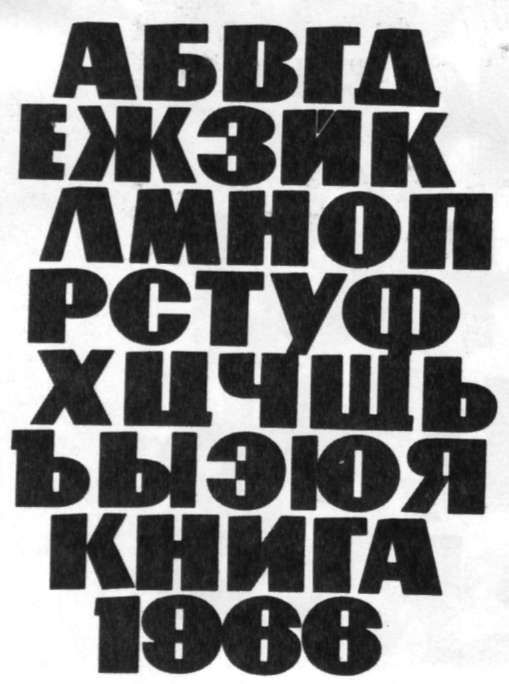
Доброго дня всем. Сегодня мы поговорим о шрифтах. И поговорим исключительно с практической точки зрения без внедрения в историю, без научных терминов и рассмотрения различных научных точек зрения на виды и подвиды шрифтов. Классификация шрифтов будет сугубо личной и субъективной, основаной только на собственном многолетнем практическом опыте.Есть такая область полиграфии, как изготовление визиток, штампов и печатей. При этом последние два вида изделий — не совсем полиграфические, но главное требование к верстальщику (наборщику) одно — хорошее знание шрифтов. Это рубленые шрифты, без засечек (таких горизонтальных палочек на «ножках» букв). Два наиболее распространенных шрифта: Ариал (Arial) и Прагматика (Pragmatica). Ариал — это универсальный виндосовский и вордо-экселевский шрифт с незапамятных времен. Поскольку во многих редакторах он стоит по умолчанию, не мудрствуя лукаво им и набирается очень многое из того, что мы называем текстом. Зачем делать лишние движения! Прагматика очень распространена в печатях и штампах. Отличается от Ариала…
Давайте сначала определимся, каким инструментом мы будем мерять шрифты. Естественно буквами, но не всеми. В русском языке их 33 штуки и мы замучаемся выверять каждую буковку. Поэтому возьмем 6 букв, наиболее показательных, на мой взгляд: С,К,Л,М,Е,А. Этого вполне достаточно, в дальнейшем вы убедитесь сами.Конечно, есть еще толщина линии шрифта, конденсированность (узкий-широкий), TTF-OTF, еще масса нюансов, часть из которых мы рассмотрим в дальнейшем.Но пока обойдемся именно этими буквами. Во всех этих шрифтах есть различия приглядитесь к таблице, к нашим шести буквам.Я перечислил самые популярные в России ( и не просто популярные, а постоянно встречающиеся в печатях, штампах, визитках и другой полиграфической продукции) шрифты ариалоподобной группы, естественно, есть много других, менее именитых, кроме того, сейчас каждый год, а то и месяц появляются все новые и новые дубликаты шрифтов с небольшими отличиями.Кстати, не существует шрифтов для CorelDraw, шрифты существуют сами по себе и устанавливаются в папку windows/Fonts, откуда уже доступны любому текстовому или графическому редактору. Просто наиболее удобно рассматривать особенности шрифтов именно в графическом редакторе, в данном случае, в свехпопулярном в России CorelDraw. Следующий раз мы разберем фрисетоподобную группу.
FontCreator
Получить программу можно на официальном сайте: www.high-logic.com
- самый популярный редактор шрифтов в мире;
- широкий функционал по редактированию и созданию шрифтов с нуля;
- возможно свободно работать с любыми форматами;
- легко найти руководства и видеоуроки по интерфейсу и работе с программой, в том числе и на русском языке;
- платная программа.
Glyphr
Скачать программу или воспользоваться сервисом онлайн: www.glyphrstudio.com
- редактор шрифтов, ориентированный на дизайн для веба;
- низкий порог вхождения и интуитивно-понятный интерфейс;
- возможно работать в онлайн-версии без установки;
- множество подробных видеоуроков на английском языке на официальном сайте;
- распространяется бесплатно.
BirdFont
Скачать программу: birdfont.org
- многофункциональный редактор шрифтов;
- возможность глубокой работы с цветом;
- распространяется бесплатно.
Приступим к работе над нашим шрифтом
У вас есть нужный шрифт и программа для редактирования, осталось немного поработать руками. При этом даже не нужно уметь рисовать, чтобы воссоздать стиль для символов кириллицы:
- Копируем аналогичные по виду буквы из латинского набора.
- Ищем похожие символы с небольшими различиями. Например, «F» очень похожа на «Г», достаточно удалить черточку посередине, а «N» легко превратить в «И», отразив по горизонтали.
шрифты разных кеглей (рис. 131).
Согласно классификации типографских шрифтов, принятой в
СССР, все шрифты делятся на пять основных групп. Такое подраз¬
деление до недавнего времени соответствовало рисункам и ассор¬
тименту типографских шрифтов, применявшихся в нашей стране.
Однако за последнее время у нас стали появляться шрифты нового
рисунка, которые нельзя отнести ни к одной из пяти групп, и число
их, несомненно, будет расти. Все это, а также изучение опыта зару¬
бежных классификаций позволяет уже теперь расширить количе¬